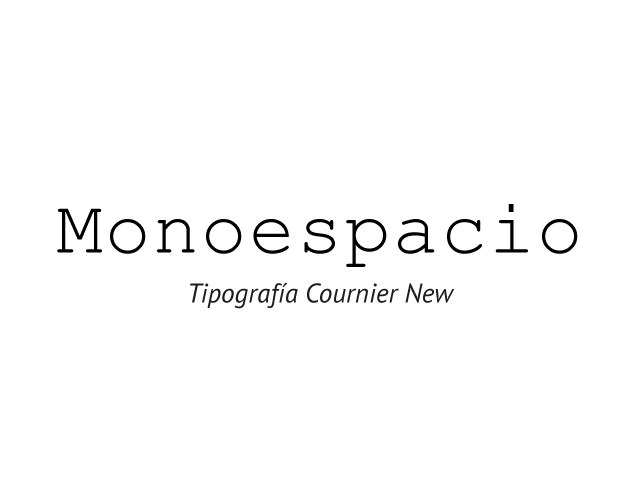
MONOESPACIO
Son familias tipográficas en las que todos los signos alfabéticos ocupan el mismo ancho, por eso es que se las llama “monoespacio”. Estas familias tienen su origen en los tipos de las máquinas de escribir. Un ejemplo de esta familia es la tipografía Courier.